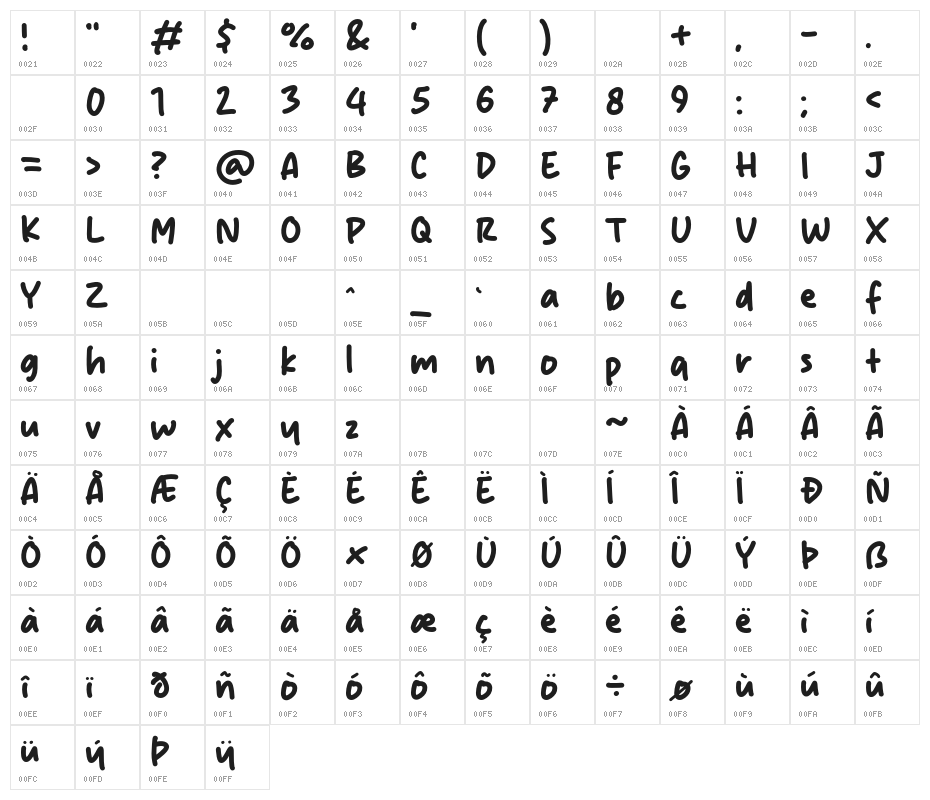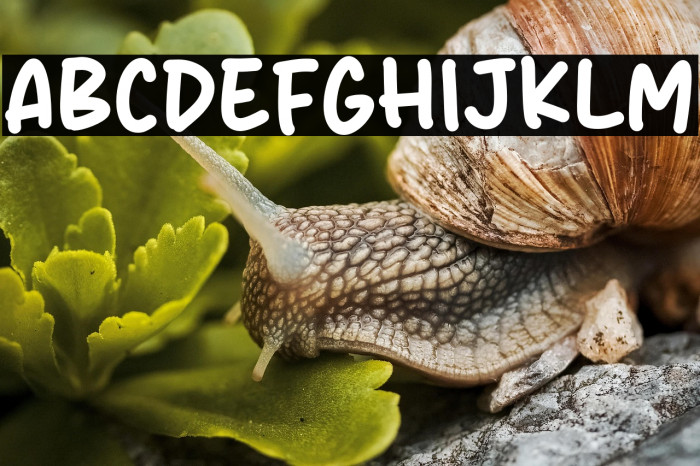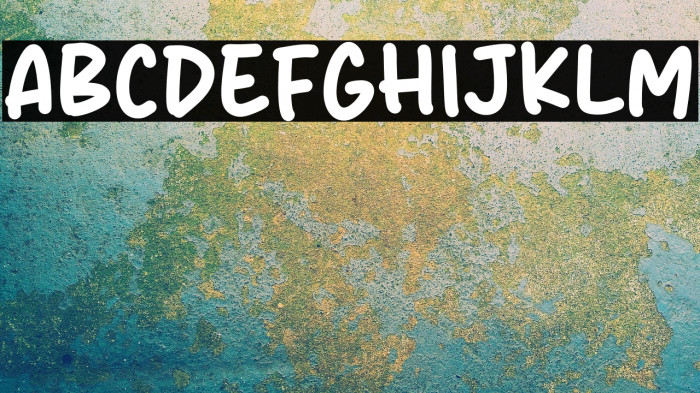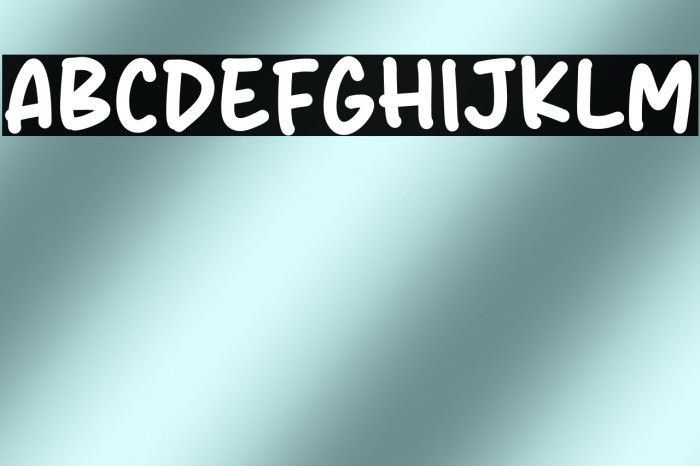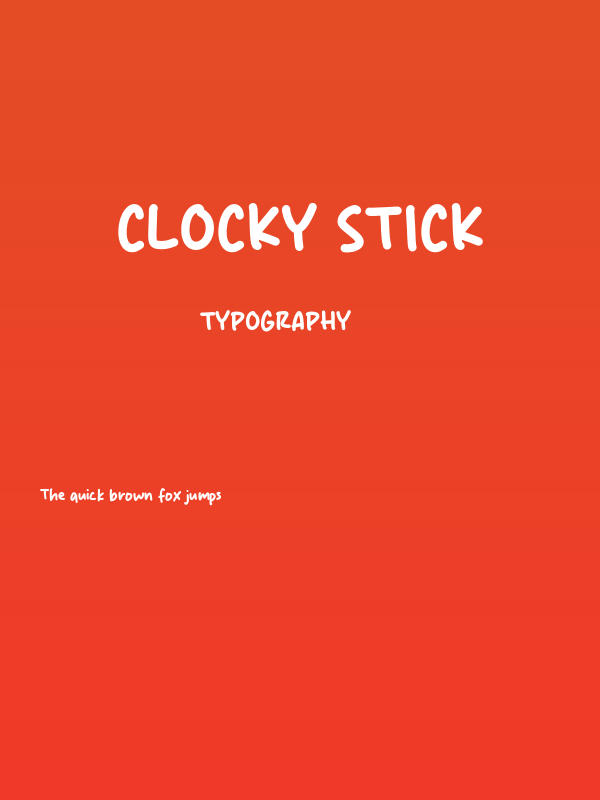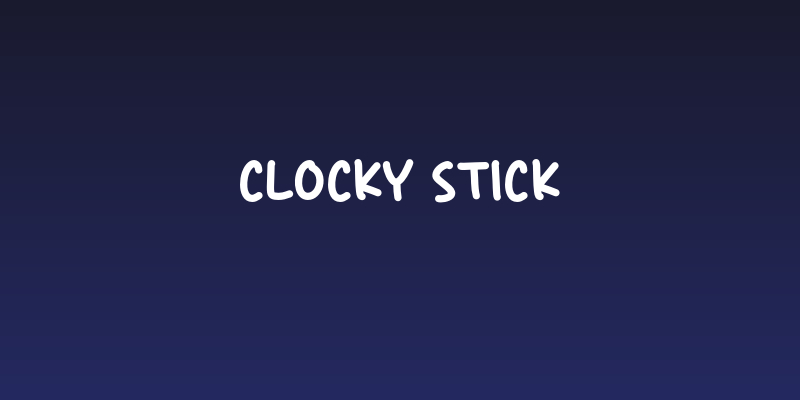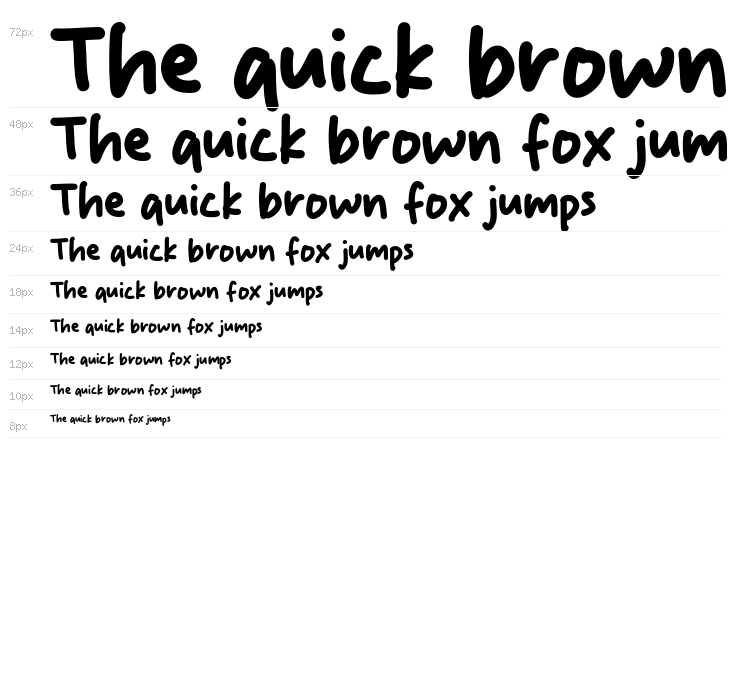
Clocky Stick Font
| Stile generale | Casual, Playful |
| Caso d'uso | Headlines, Logos, Informal Text |
| Progetti proposti | Ideal for greeting cards, children's books, playful branding, and social media graphics. |